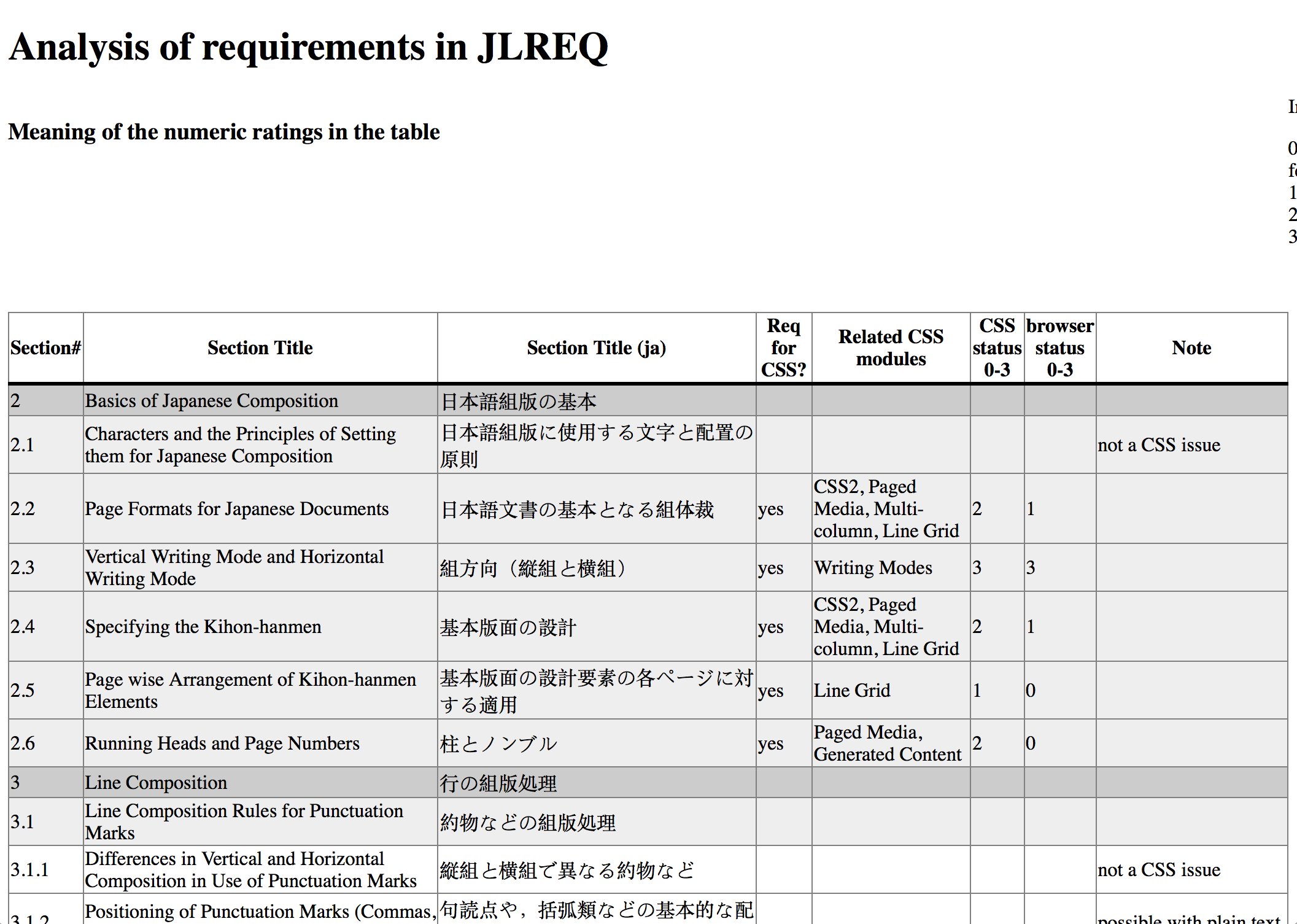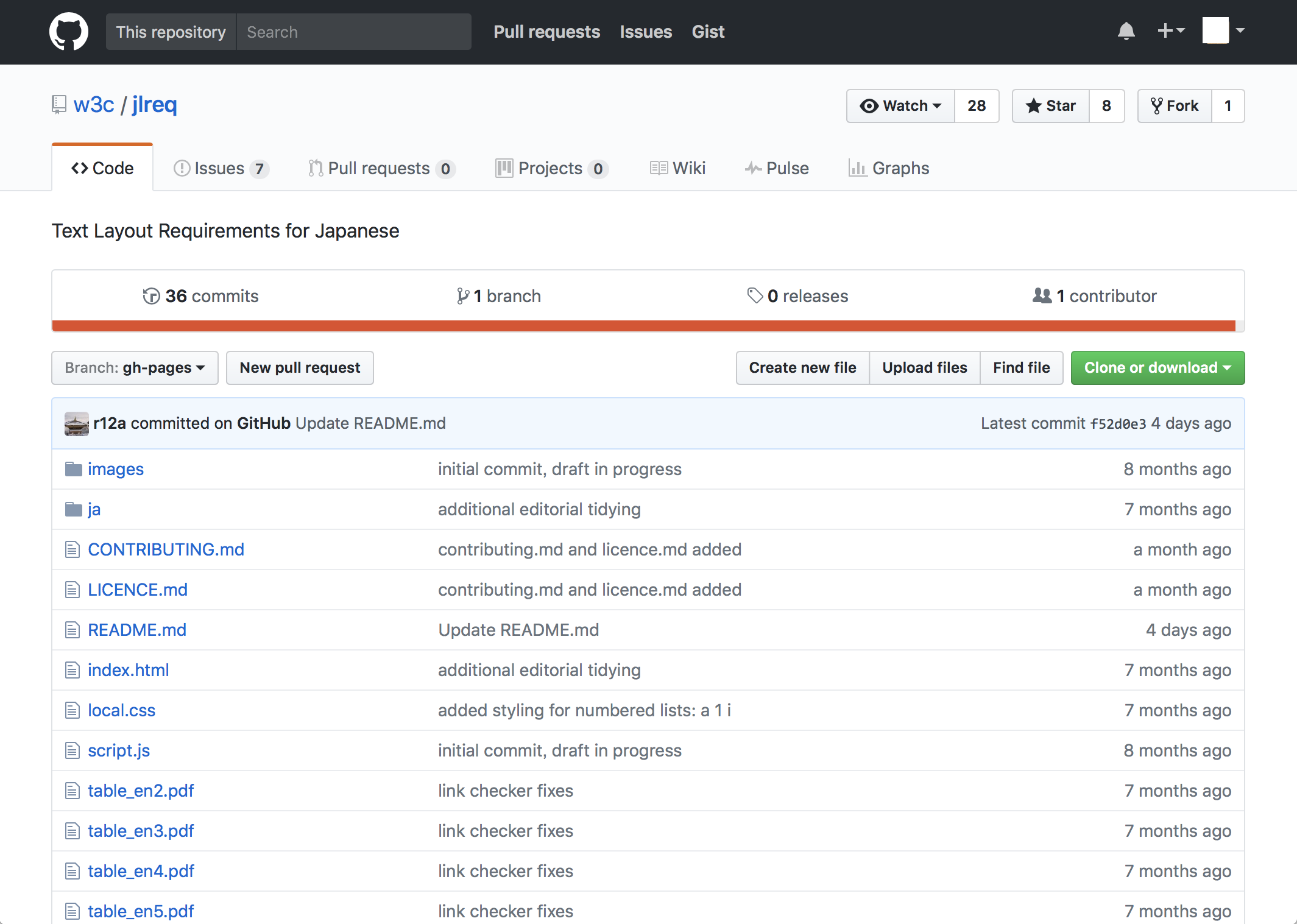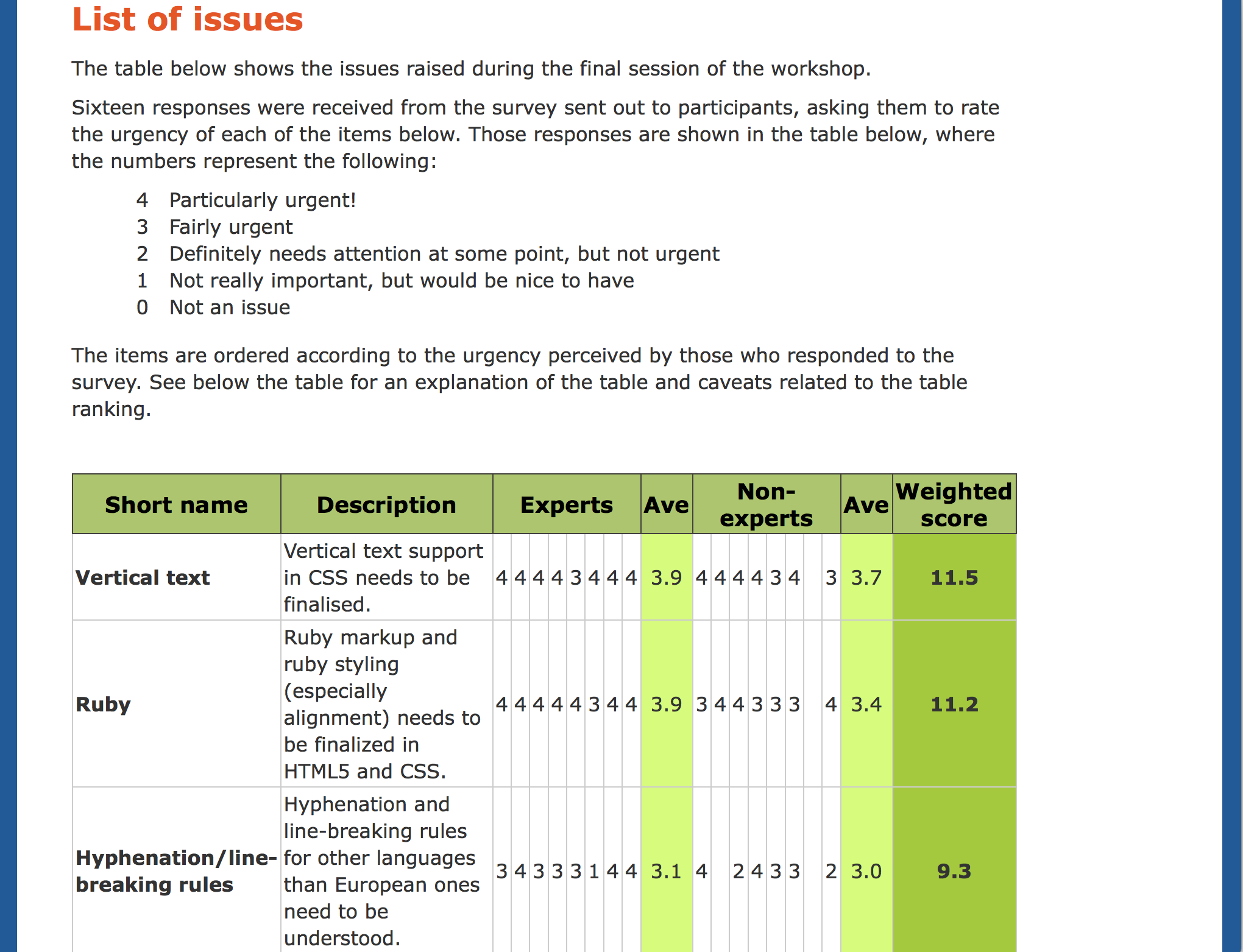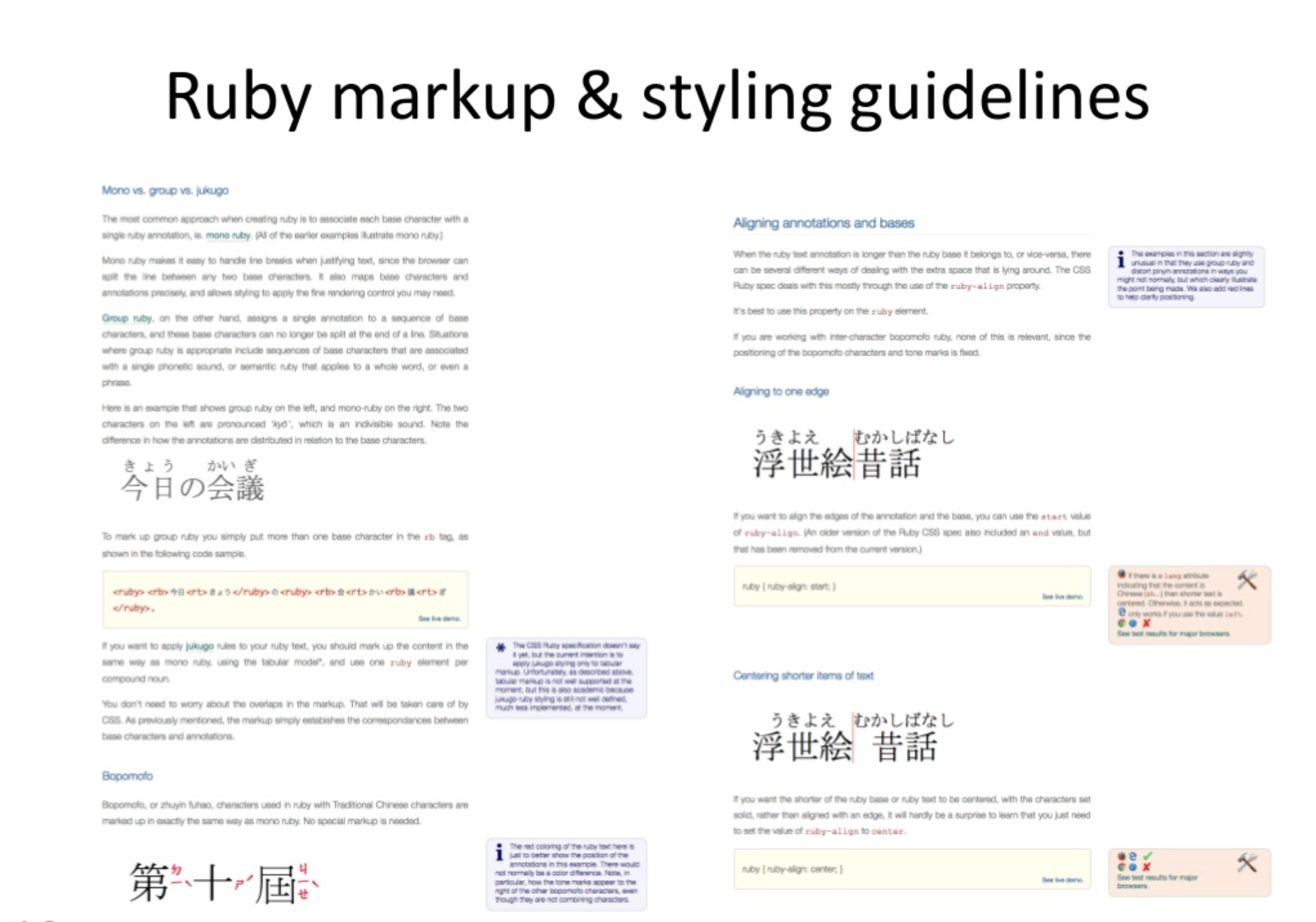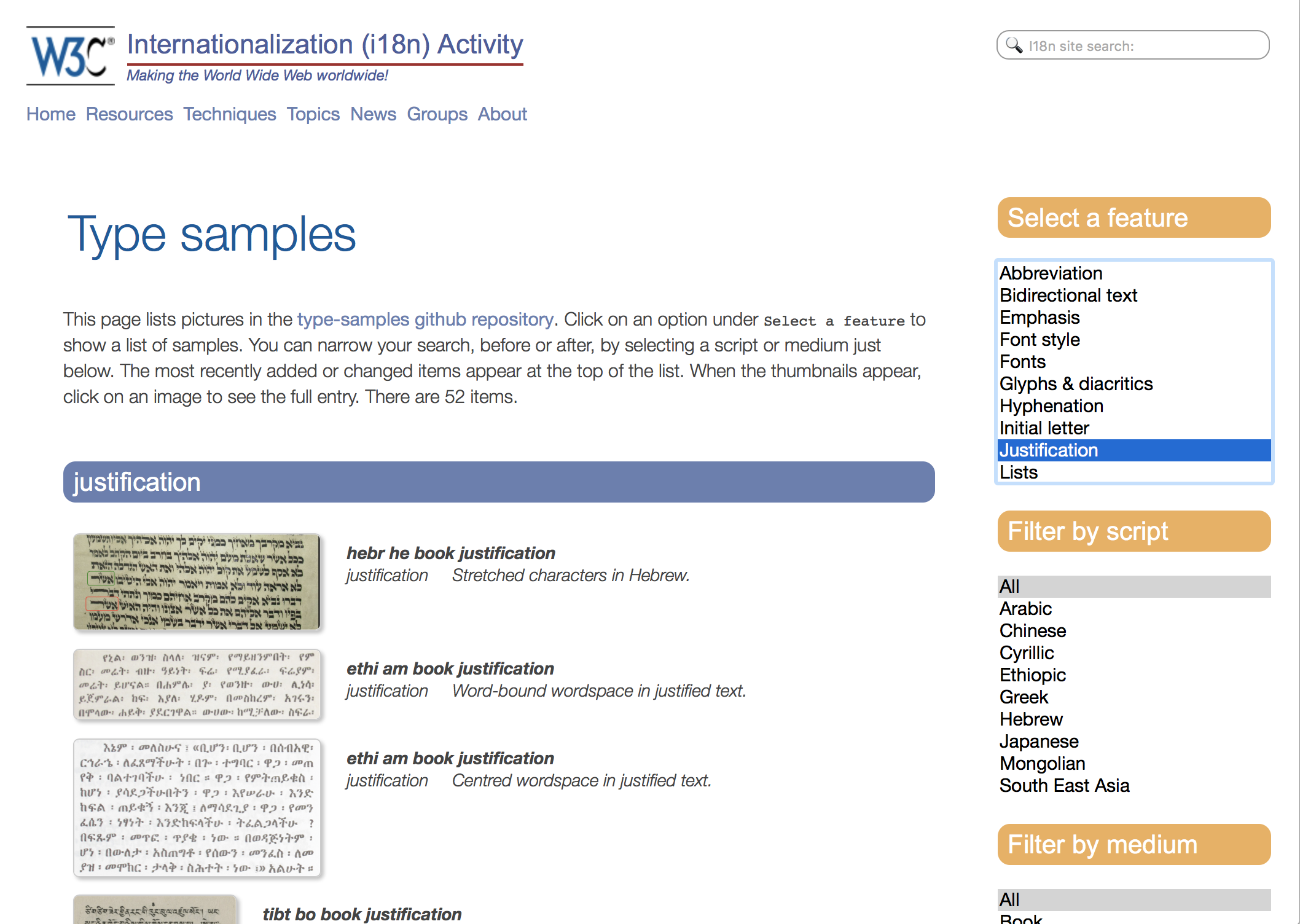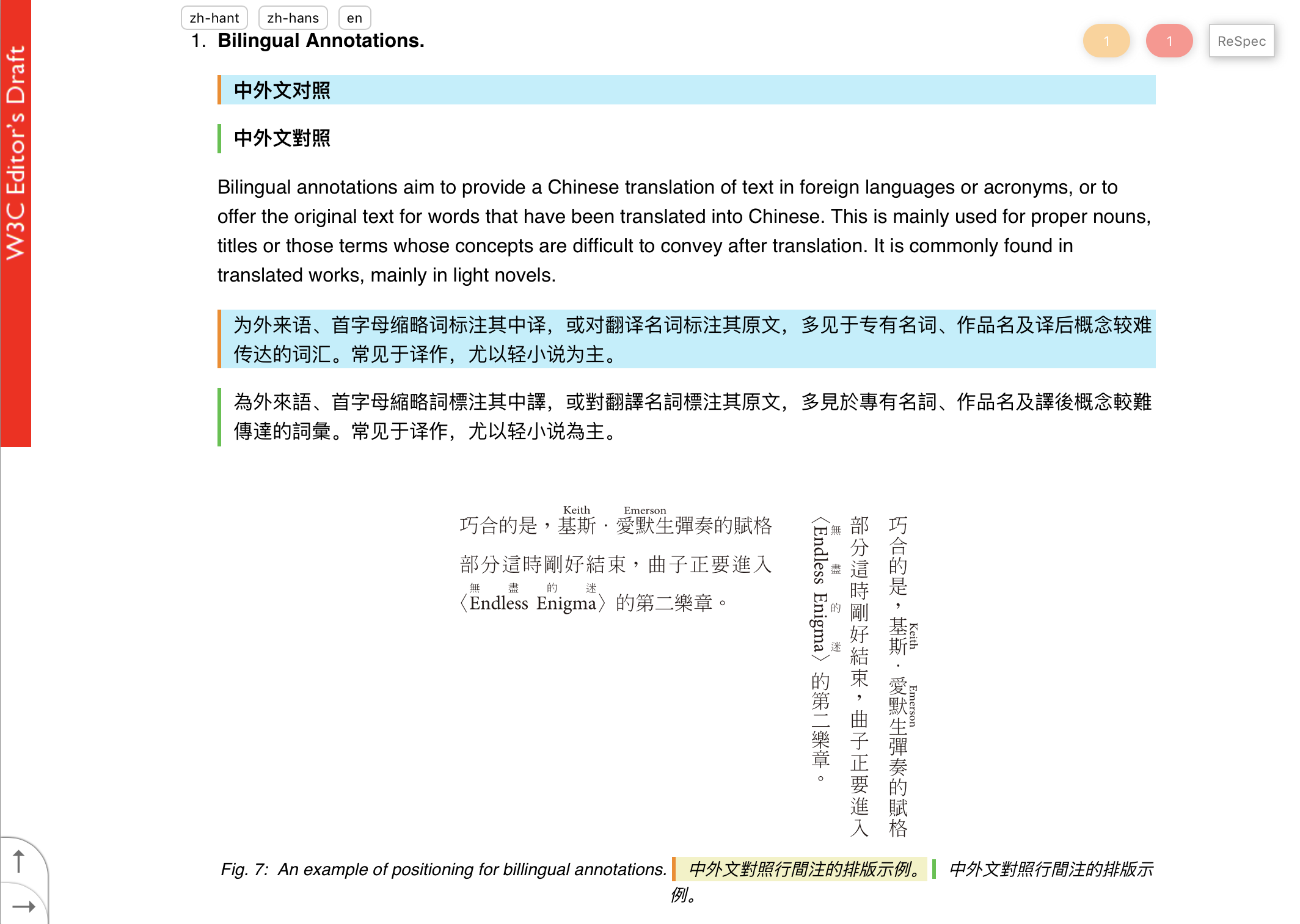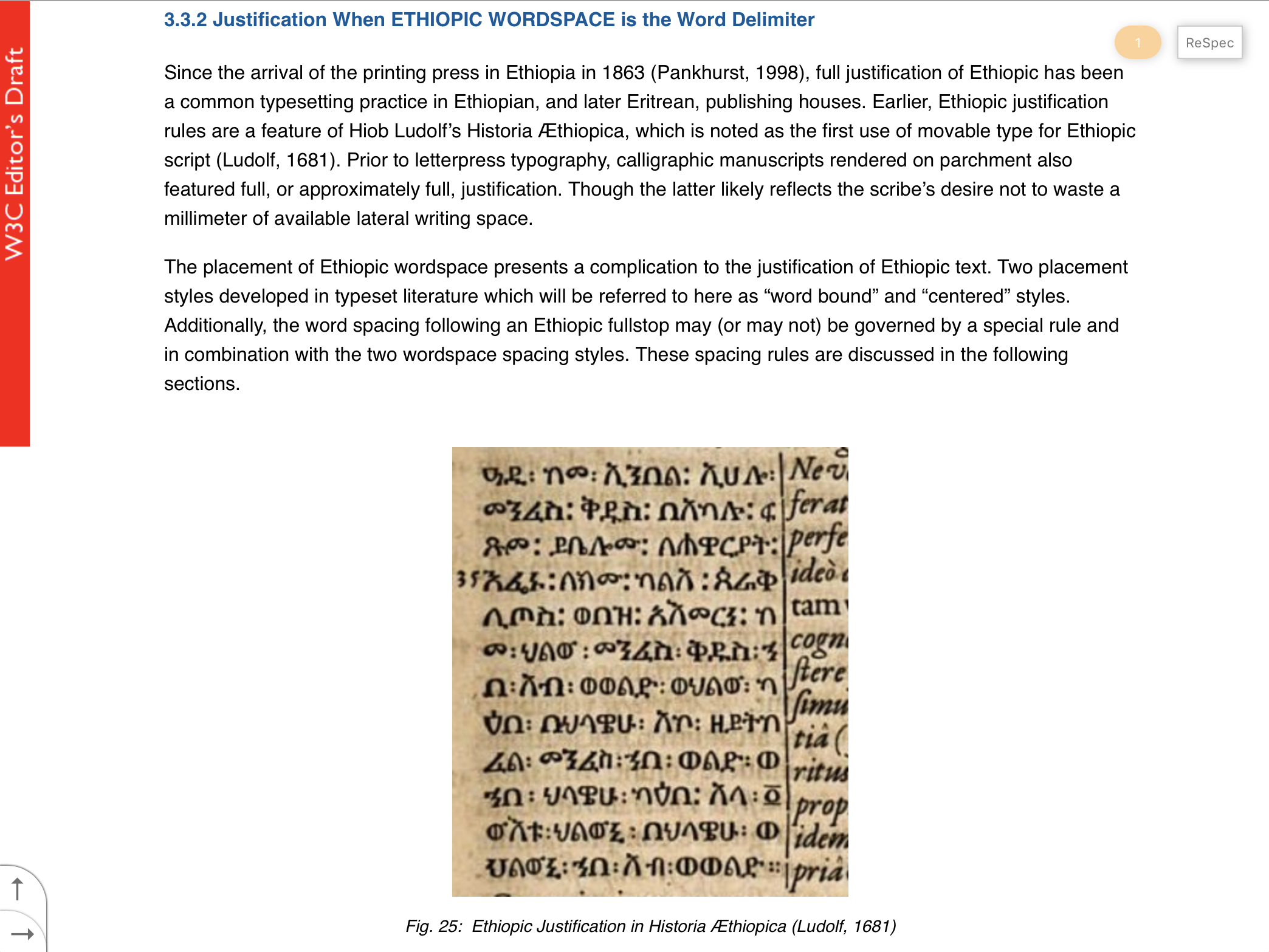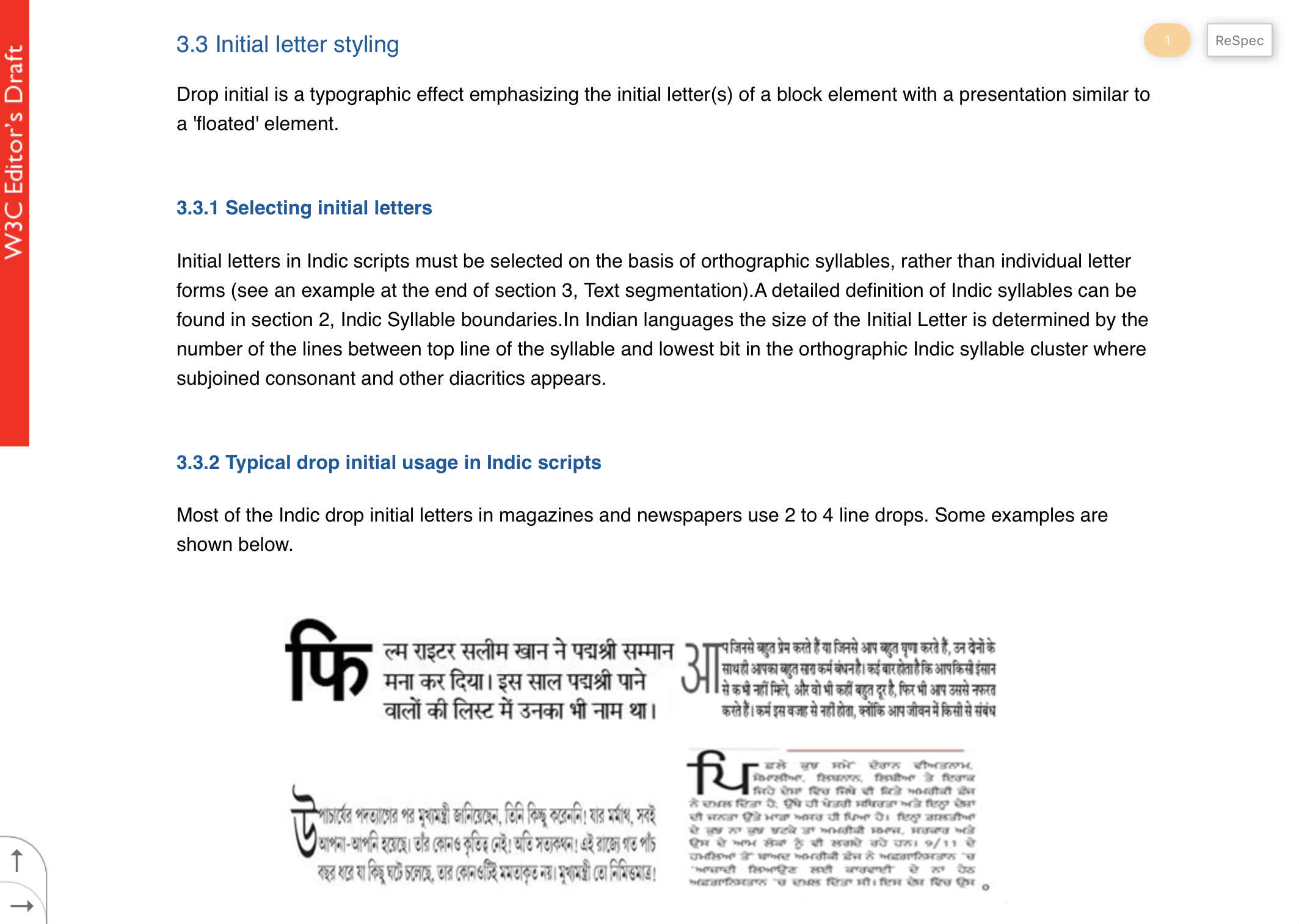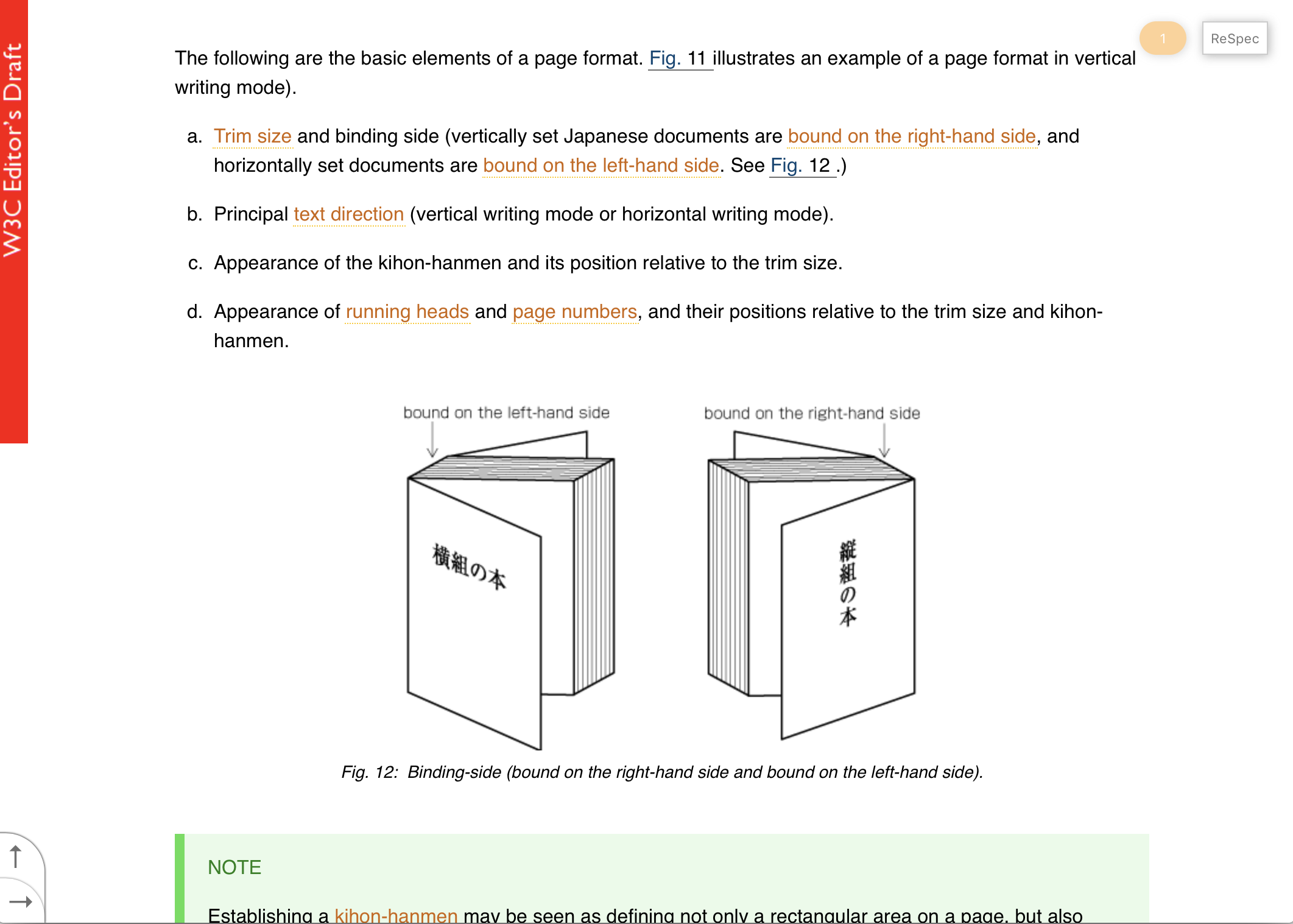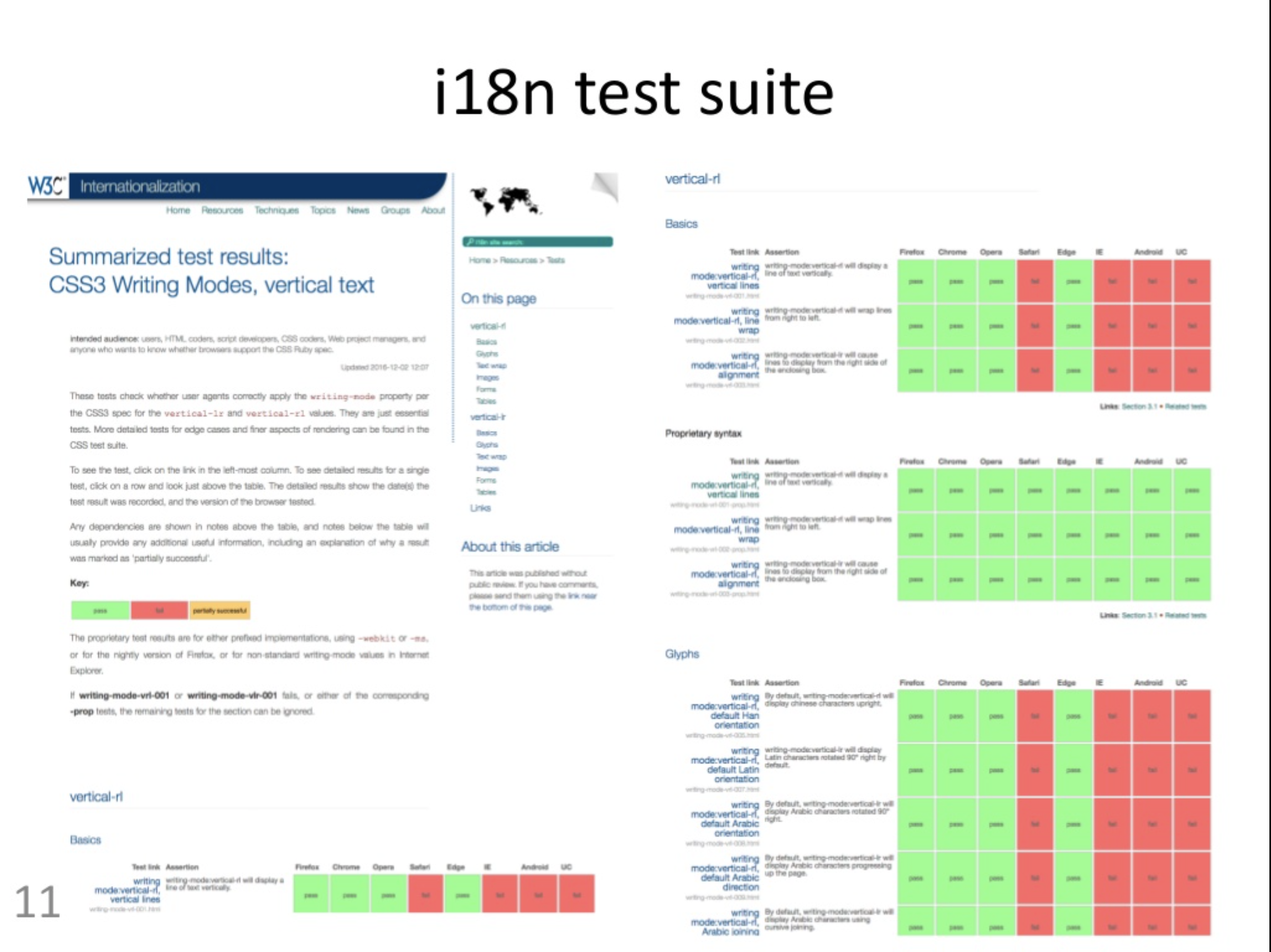
本文是萬維網聯盟(World Wide Web Consortium,簡稱 W3C)國際化工作組(i18n WG)組長 Richard Ishida 先生在 2017 年 3 月 17 日在日本電子出版協會(JEPA)舉辦的講座「《日文排版需求》的今天和明天,以及 CSS 日文排版」上通過 Skype 用英文發表的演講。雖然此演講是面向日本聽眾講解關於《日文排版需求》的內容,但考慮到該文檔在 W3C 國際化工作中的重要地位,並且對《中文排版需求》有重要影響,這場講座的內容對於中文社區也非常有意義。正如日本電子出版協會 CTO 村田真先生所說:「W3C 標準不是坐等着讓誰做給我們的,而是靠大家的力量一起做出來的!」作為《中文排版需求》編輯之一,筆者經授權在此提供翻譯版本,目的是希望讓中文社區了解日文以及其他文種國際化工作的動態,認識到中文排版需求與日文工作的差距,呼籲中文社區有所思考並積極行動起來,為更豐富的中文電子環境做出貢獻。
正如大家所知,作為日本多名字體排印專家多年來活動的成果,《日文排版需求》(Requirements for Japanese Text Layout, JLReq)文檔最新版已於 2012 年 4 月發布。雖然其中的很多需求最初均來自書籍出版的使用案例,但大多數需求仍然與 Web 網頁,尤其是網絡上的電子書和其他分頁格式密切相關。這份文檔一直是 W3C 標準、網頁以及電子書開發者非常有用的需求來源。
因為與技術非相關,《日文排版需求》為大家提供了一個非常有用的基礎,用來評估 Web 平台的狀態是否能滿足日本出版物的需求,而這份文檔在未來也應該會繼續發揮作用。最近,《日文排版需求》文檔(英文和日文)被移植成 ReSpec 格式並添加到 GitHub 庫上,這樣不僅可以方便後續工作,而且還可以更簡單地抓取並管理文檔中的各種問題。
一旦我們對「需求」有了一個很好的描述,那麼下一步就應該運用這些需求,去評估其與特定技術的特性集之間的差距。最常見的情況下,這是由瀏覽器、電子書閱讀器的實現者,或者由規範的開發人員針對性地去完成的。但在其他情況下,會採用一些更富有協作的方式進行。
例如,2013 年在東京舉辦了一場題為「電子書與 i18n:電子書更為豐富的國際化」的研討會,會上有大量的日本觀眾參與。會議報告中的「優先問題列表」指出,研討會參與者關注度最高的兩個問題是對「豎排」和「注音假名」(ruby)的支持。其他受關注點還包括,針對其他文字編撰類似《日文排版需求》那樣的需求文檔,以及對換行規則、強制換行(泣き別れ/nakiwakare)1、縱中橫(縦中橫/tate-chu-yoko)更好的支持等等。
目前,我們正在開展針對其他文種的需求撰寫工作。以《日文排版需求》這樣的標杆文檔類似,現在已經發布了 CLReq 即《中文排版需求》、KLReq 即《韓文排版需求》、ALReq 即《阿拉伯系文字排版需求》、ELReq 即《埃塞俄比亞文排版需求》、ILReq 即《印度系文字排版需求》、TLReq 即《藏文排版需求》(這份文件僅是一份初期草案),而 HLReq《希伯來文排版需求》馬上就要問世。
在那次會議之後,針對「豎排」和「注音假名」的標準化工作也一直在進行。儘管還需要繼續完善,但是這些特性在瀏覽器方面已經出現了令人鼓舞的一些進步。《CSS 書寫模式(第三級)》規範目前已處於「備選推薦」(CR, Candidate Recommendation)狀態2。這份文檔和《CSS 文字模塊(第三級)》《CSS 注音排版模塊(第一級)》 等等其他文檔一樣,都從《日文排版需求》提供的信息里獲得了極大益處。
今年 1 月,日本一些組織的代表向 W3C 提交了一份名為《使用網頁技術進行日文字體排印的當前狀態》的「成員提交」件,其中研究了 CSS 和 HTML 針對日本的分頁文檔排版是否足夠。他們具體分析了兩份文檔提出的需求:一份是 W3C 的《日文排版需求》,另一份是日本電子書籍出版社協會(The Electronic Book Publishers Association of Japan, EBPAJ/電書協)的《EPUB3 日文排版要求表》。這份提交報告顯示了哪些需求已經由哪些 CSS 規範所覆蓋並為主流瀏覽器所支持。報告的結論是,現在的 CSS 對日本分頁文檔的支持還是相當不錯的,如果有更多的模塊(尤其是對分頁媒體)能被完全開發並實現,則會更好。
以上提到的這些發現,對於縱觀整個形勢非常有用。而且經過長時間不斷維護,並與「特性優先度」和詳細研究等工作相結合,則會有更大的價值。W3C 最近的一些開發工作能助此一臂之力。
今年 3 月 13 日,W3C 國際化工作組發表了一篇題為《中日韓蒙豎排風格化》的文檔。這份文檔可以幫助內容創作者們利用 CSS 去創建中文、日文、韓文和蒙古文的豎排文本。不僅如此,文檔里還詳細描述了在主流瀏覽器里哪些特性可以實現、哪些不行,並提供了一些測試,讓用戶在自己的瀏覽器中運行。這其實是提供了非常有用的下一步工作,從用戶的角度總結了當前狀態下瀏覽器對豎排文本支持的情況。而實際上,編譯這篇文章初期素材的過程也同時影響了《CSS 書寫模式》規範的開發。
現在我將列出 W3C 國際化工作組最近所做工作的一些進展,其中也包括支持日文字體排印相關特性的部署。
- 《注音標記》一文最近已經由國際化工作組發布。此文告訴內容創作者如何為注音(ruby)做標記。和前面提到的關於豎排的文檔一樣,這份文檔也帶有示例,讀者可以用來測試他們的瀏覽器的行為;同那份文檔一樣,這份文檔的撰寫同樣影響了 CSS 規範的開發。
- 《注音風格化》正在籌備中,這份類似的文檔將會根據 CSS 注音規範講述注音的位置屬性。和豎排那篇文章一樣,這篇文章也將提供「哪些瀏覽器支持哪些特性」的詳細信息,並附有測試文件的鏈接。
- 為「網頁平台測試庫」(Web Platform Test Repository)開發了一套範圍更廣的測試。這些測試也是國際化測試套件的一部分,除了測試鏈接還會顯示主流瀏覽器的實際效果。相關測試包括:
- 國際化工作組剛剛發布了一份《國際文字排版與字體排印索引》文檔的「首次公開工作草案」(FPWD)。這份文檔針對的是瀏覽器實現者和規範開發人員,為他們提供了有關如何支持來自世界各地的各個文種、書寫系統的字體排印特性,並且還提供了相關規範信息、測試以及有用的文檔和論文。今後還將 CSS 規範鏈接到這份文檔里,以便讓實現者可以找到有關文字如何工作的詳細信息。預計這份《索引》文檔將會持續更新。
這份文檔不僅可以幫助人們找到針對某個文種(比如用於日文)的需求信息,而且還可以(向文字需求的提供者)指出當前使用某個文種時存在的問題,(向規範和瀏覽器實現者)提出在規範和瀏覽器中實現某些特性的要求。例如,目前就有人在詢問
text-decoration-skip:ink
應該如何用於表意/CJK 文字,還有的人在問在「自動隱藏注音」中強調標記應該有什麼樣的行為。這是我們首次提供了這樣一種方式,針對某個特定文種如何運作,以及針對該文種的各種實現請求的進展,都可以對當前存在的問題進行追蹤。 - 剛剛提到的《字體排印索引》還為一個全新的「字體樣本 GitHub 庫」提供了索引。這個庫收集了許多字體排印的用例圖片,可用於示例、測試或插圖。例如裡面有圖像在解釋日文的「翻轉列表式樣」特性,還有解釋「行內注」(割注/warichu)的插圖等等。
- 上述這些材料和索引,對於最近一些 CSS 和 HTML 之外涉及日文字體排印的新標準化工作也很有作用。去年,國際化工作組審查了 WebVTT 規範,我們目前正在與 TTML2(時序文本標記語言第二版)的創建者進行討論。這兩個規範都在為日本市場準備支持豎排和注音假名,但他們都需要幫助以確保指定的特性能夠滿足日本用戶的實際要求。
- 我們預計在未來,其他規範也會需要類似的建議,並且國際化工作組目前正在考慮為「注音標記」編輯定義一個內容模塊,將《注音標註》(Ruby Annotation)規範和「HTML 注音內容模塊」之間的差異聯繫起來。
支持豎排、注音假名和日語的其他功能的工作一直在前進,但仍有一些功能需要瀏覽器廠商的承諾來完成所需的支持。例如,雖然豎排文本大多數都已經實現,但對於優秀的日文豎排來說,text-orientation
(文本方向)中 upright
(直立)值是必須的,但目前瀏覽器的支持還很不好。同樣,支持 text-combine-upright
(縱中橫)的 digits
(位數)值也可以讓內容創作者變得更輕鬆,但依然沒有得到瀏覽器的廣泛支持。目前大多數瀏覽器對「雙邊注音假名」的支持都需要使用 HTML5 嵌套 ruby 語法,而不是採用更直接、可擴展的 ruby 內容「表格模塊」。而 ruby-position
(注音位置)也需要更好的支持,更不用說「注音文字對齊」、「注音文字層疊處理」等更高級的技術了。其他特性也是如此。
但是請注意,目前的一個主要障礙是瀏覽器、閱讀器的實現者有太多的事情要做,我們需要說服他們去填補這些差距。通常來說,說服他們最好、也是唯一的方式,是讓那些受影響的用戶社區為實現提出一個強有力的理由。單靠邏輯參數是不夠的。瀏覽器實現的工作人員需要認識到,不支持這些特性的確會對應用軟件的使用造成明顯的困難。
因此我建議,在日文特性支持方面,我們要繼續分析的差距在哪裡,但是要從一個更細緻的層面去做;然後我們還要為處理這些差距進行優先度處理並創建專案,還要比以前更有規律地定時去做,這樣我們才能找到一些方法,向他們展示用戶、內容創作者和開發者的痛點在何處,這樣才可以說服實現者在瀏覽器和電子閱讀器中加入那些缺失但卻需要的特性。
日本的字體排印專家也可以考慮根據 W3C 國際化興趣組(現在針對這樣的小組我們已經有一個標準框架)對「日文排版工作任務組」進行重組,以便開展《日文排版需求》的各種編輯、勘誤或者可能是一些實質性修改。
而且,與《中文排版需求》(還可能包括韓文,如果還有活躍的專家)協調工作也非常有價值,這對於諸如豎排文本、注音、換行、文本裝飾等特性應該如何工作會有一個更為清晰的認知。在標準化過程中,也有一些微小的差異需要權衡。
主要建議
- W3C 國際化工作組針對使用日文(和其他)文種特性提供詳細指南方面的工作應該繼續,除此之外還包括配套的索引、庫和測試工作。這是非常有意義的。
- 其他文種(不僅是中文和韓文)「需求文檔」的編撰工作都從《日文排版需求》工作里得到了很多重要的相關益處,我們應該繼續支持並監管那些工作。
- 日文社區應考慮重新建立《日文排版需求》工作組,由 W3C 國際化興趣組對文檔進行維護。
- 日本社區越來越多地參與支持日文特性相關的 W3C 和 WhatWG 標準的評審,這將對改進這些特性在規範和實現中的應用有極大幫助。
- 根據《W3C 流程文檔》的規定,一份正式的 W3C 推薦標準的狀態分為:「首次公開工作草案」(FDWD, First Public Working Draft)、「公開工作草案」(PWD, Public Working Draft)、「備選推薦」(CR, Candidate Recommendation)、「提案推薦」(PR, Proposed Recommendation)直至成為最後的「推薦」(W3C Recommendation);另一方面,包括《中文排版需求》在內的「需求文檔」不屬於 W3C 推薦標準,而是屬於「工作組筆記」(Working Group Note),目的是為推薦標準制定提供參考,這類文檔只有「首次公開工作草案」(FDWD)、「工作草案」(WD,比如目前《中文排版需求》2015 年 7 月 30 日正式發布的狀態)和正式發布的「筆記」(Note,比如目前《日文排版需求》2012 年 4 月 3 日正式發布的狀態)這兩種狀態,另外還有若干未經正式發布的「編輯者草案」(Editor’s Draft)。